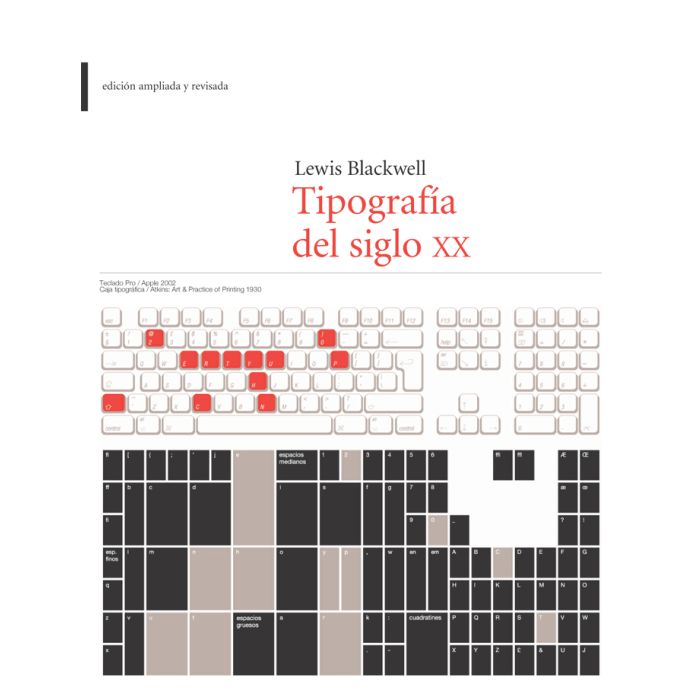
Tipografía del siglo XX
Un libro de Lewis Blackwell
En un análisis estructurado por décadas, Tipografía del siglo xx examina los principales aspectos que han dado forma a la historia del diseño tipográfico y, en los últimos tiempos, también del diseño gráfico. El libro muestra de qué modo las actuales corrientes tipográficas forman parte de un continuo proceso de cambio que se va tejiendo a lo largo de las diferentes décadas. Entre los temas tratados se encuentran la llegada de la producción de masas, el surgimiento de la figura del director de arte, la aparición de la retícula (y su posterior abandono), la llegada de los medios no impresos y el lanzamiento de los Macintosh, con la consiguiente aparición de una nueva generación de diseñadores que han visto cómo la tecnología digital facilita su modo de trabajo.
En la década de 1990 la tecnología digital dio origen a una revolución en el diseño gráfico y en la práctica tipográfica. Esta edición revisada del clásico estudio de Lewis Blackwell actualiza la historia analizando los principales avances introducidos por la revolución digital. Entre otros puntos, Blackwell examina el desarrollo de tipos para pantalla y otras innovaciones relacionadas con la aparición de Internet como un nuevo medio global. No obstante, el autor expone en la introducción algunos de los retos a los que se enfrentan los diseñadores tipográficos y los usuarios en el nuevo milenio, dado que también existen aspectos negativos en las condiciones en las que los diseñadores trabajan actualmente.
Además de contar con más de 300 ilustraciones, el libro reflexiona sobre la cultura de la experimentación en el diseño tipográfico contemporáneo y presenta de forma clara su contexto histórico. Por todo ello, la presente obra proporciona a los diseñadores, estudiantes y al público en general una guía completa y de fácil comprensión sobre la tipografía del siglo XX y las cuestiones fundamentales que condicionarán la práctica tipográfica en el futuro.
En la década de 1990 la tecnología digital dio origen a una revolución en el diseño gráfico y en la práctica tipográfica. Esta edición revisada del clásico estudio de Lewis Blackwell actualiza la historia analizando los principales avances introducidos por la revolución digital. Entre otros puntos, Blackwell examina el desarrollo de tipos para pantalla y otras innovaciones relacionadas con la aparición de Internet como un nuevo medio global. No obstante, el autor expone en la introducción algunos de los retos a los que se enfrentan los diseñadores tipográficos y los usuarios en el nuevo milenio, dado que también existen aspectos negativos en las condiciones en las que los diseñadores trabajan actualmente.
Además de contar con más de 300 ilustraciones, el libro reflexiona sobre la cultura de la experimentación en el diseño tipográfico contemporáneo y presenta de forma clara su contexto histórico. Por todo ello, la presente obra proporciona a los diseñadores, estudiantes y al público en general una guía completa y de fácil comprensión sobre la tipografía del siglo XX y las cuestiones fundamentales que condicionarán la práctica tipográfica en el futuro.